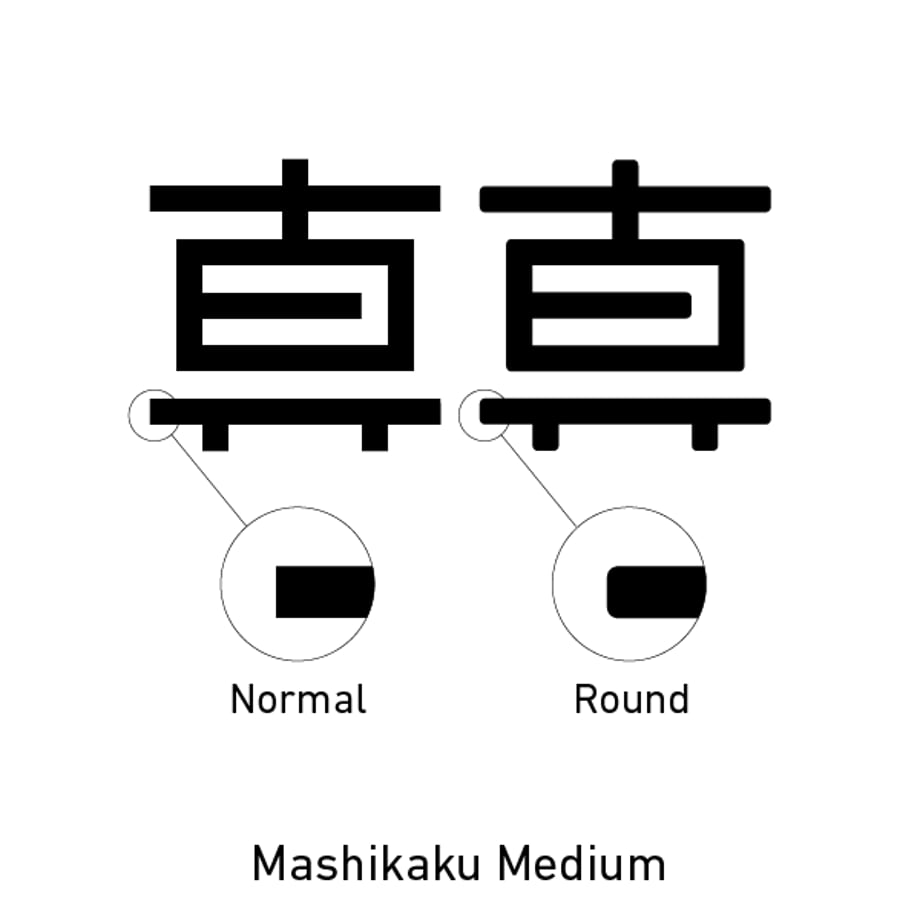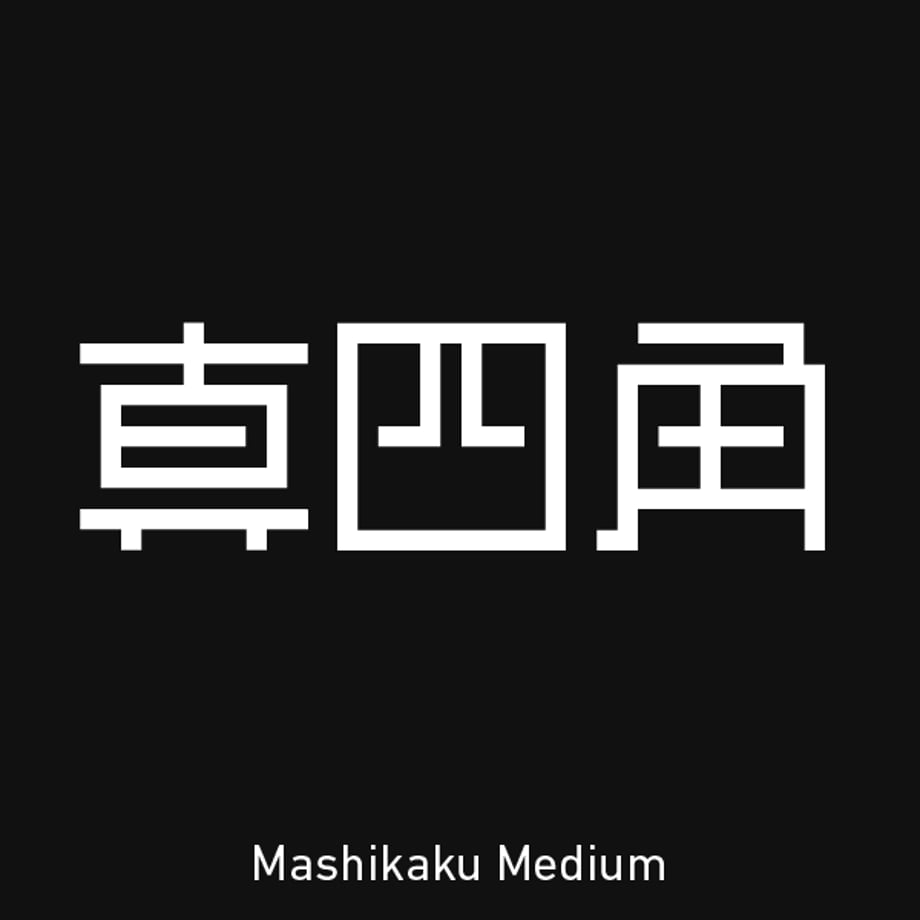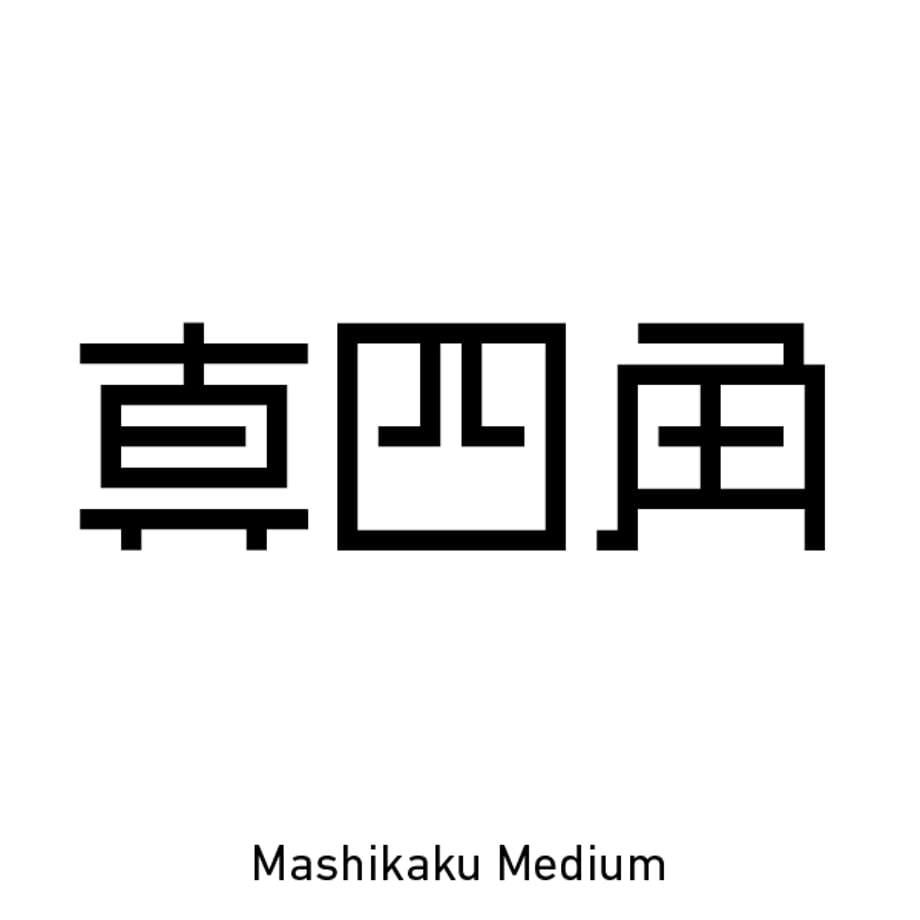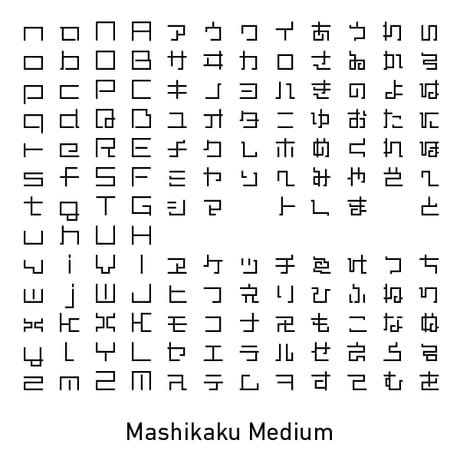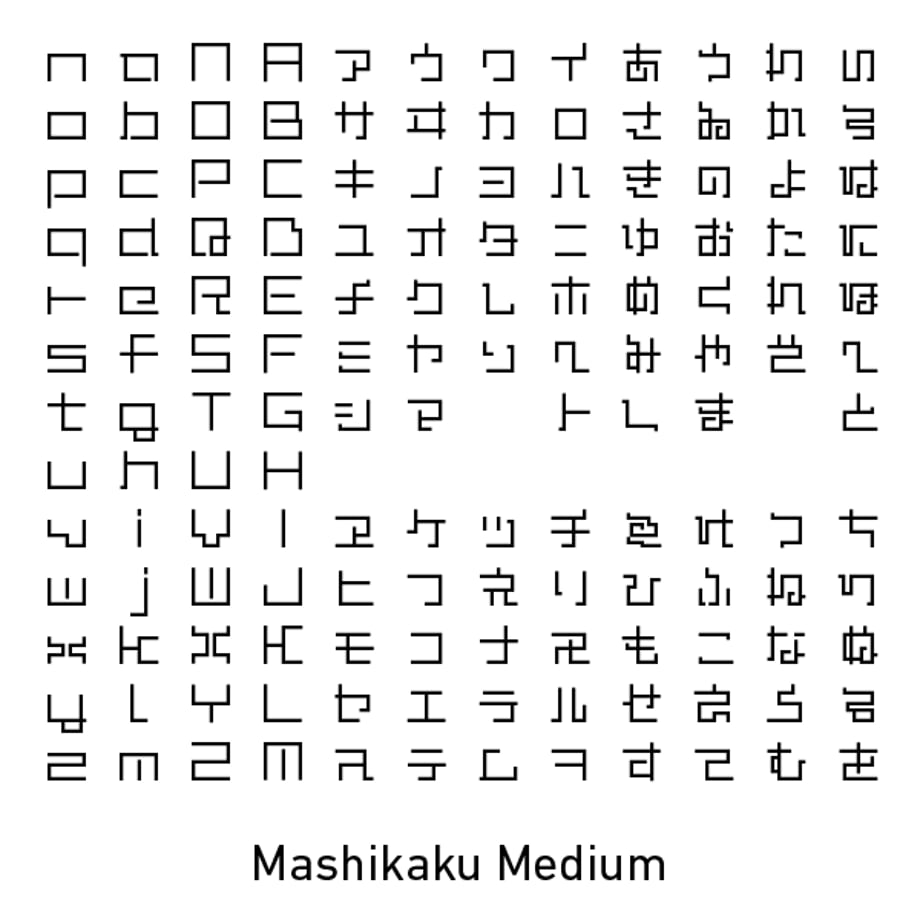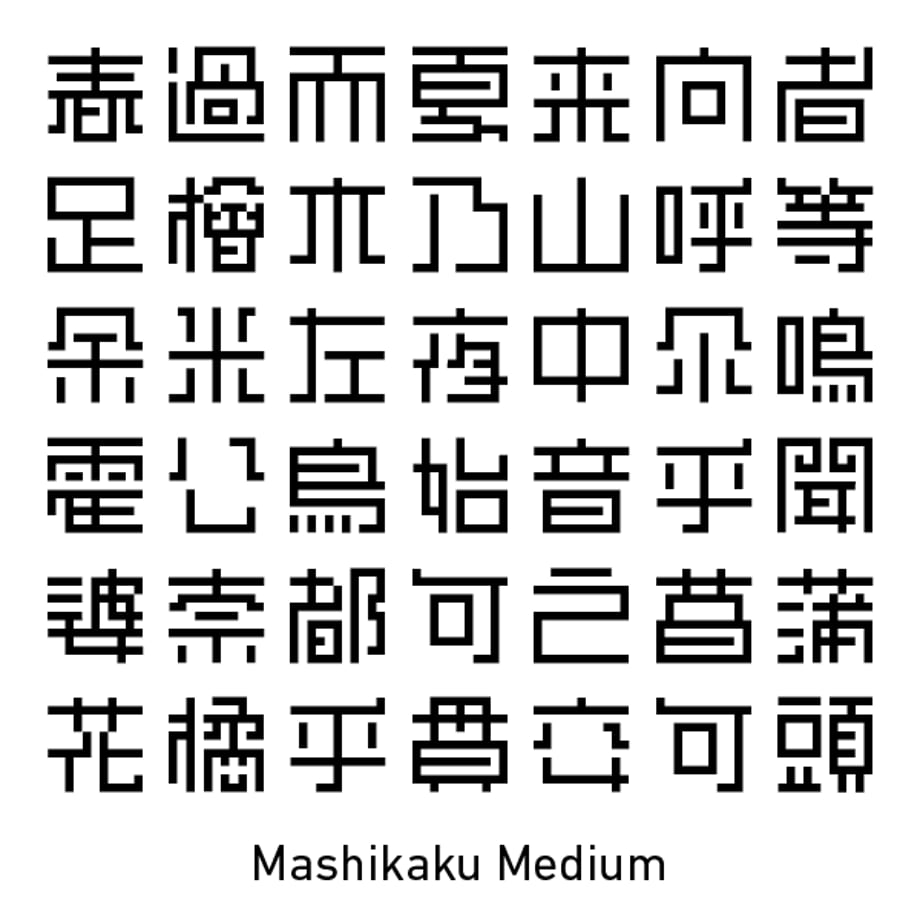
真四角書体 CJK(Mashikaku CJK)- Medium
真四角書体は、江戸文字「角字」にインスパイアされています。正方形の中に水平・垂直の線のみで構成される図形的なスタイルを踏襲しながら、現代の生活空間に自然となじむようにシンプルで親しみやすいデザインの書体です。
2026年3月のver.5(CJK Edition)アップデートでは、収録漢字を約22,000字に拡充し、9種類のウェイト展開に進化。日常利用からプロフェッショナルな制作まで、幅広くお使いいただけます。
スタイル:Normal(スクエア), Round(ラウンド/角丸)の2種を同梱